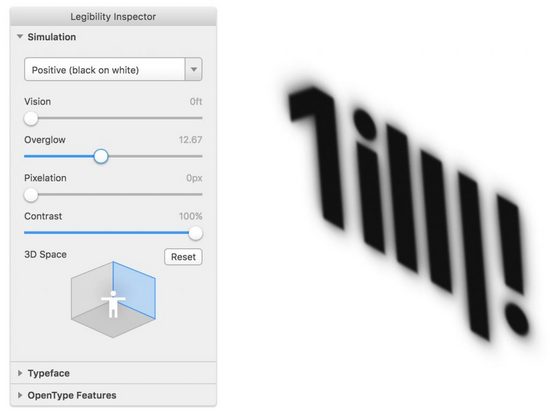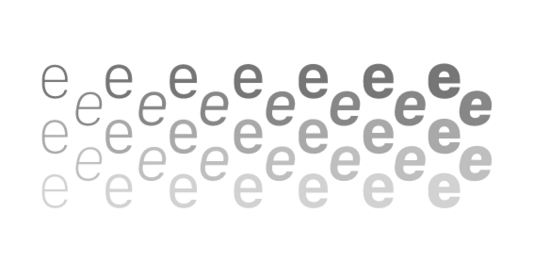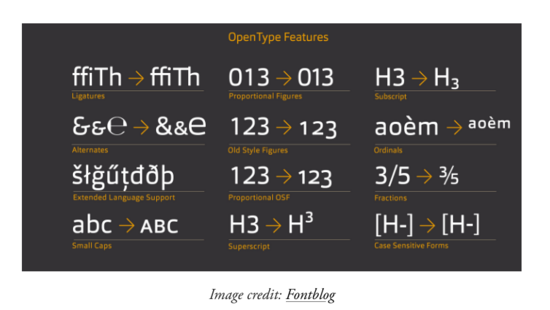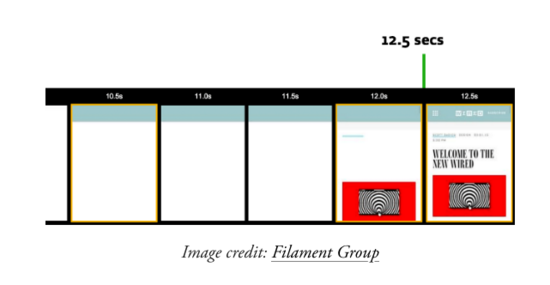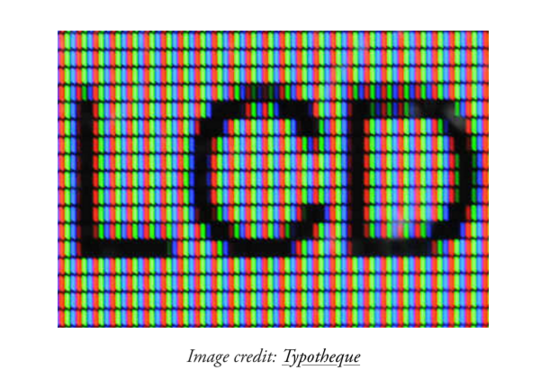
界面设计中,关于字体设计的10 个锦囊
字体作为界面设计的一个元素,对用户的阅读体验起着至关重要的作用。本文是 UI 设计师 Viljami Salminen 分享的用户界面字体设计的基本规则和技巧。
早在 2004 年,我才刚开始工作的时候,sIFR 非常火。sIFR 是由 Shaun Inman 开发、可以电影短片中嵌入定制字体的一种技术,它能被 JavaScript 和 CSS 调用。当时,sIFR 基本上是唯一一种能在 Firefox 或 Safari 浏览器中使用定制字体的技术。随着 2007 年 iPhone(不需要 flash)的推出,基于 Flash 格式的这种技术很快就过时了。
2008 年,浏览器终于开始支持新的 CSS3 字体设计规则了。早在 1998 年,这种字体设计规则就被写入 CSS 标准中了,但后来被移除了。我还记得,当我说服我的一个客户使用这种新的字型规则时候的兴奋心情,当时,浏览器已经开始支持能够提升用户体验的「渐进增强(Progressive Enhancement)」技术了。
自从涉足这个行业,我开始越来越喜欢研究字体,以及与字体设置中相关的微小细节。在这篇文章中,我打算分享一些我了解到的基础知识,希望能为用户界面的字体设置提供帮助。
第一代GUI
虽然字体的历史可以追溯到大约 5000 年前,但是图形用户界面的出现还不到 40 年。一个重要转折点发生在 1973 年,Xerox 推出了计算机 Alto,大体上奠定了今天图形用户界面的雏形。当时 Alto 被视作是计算机的未来,在 10 年之后,同类 GUI 产品才进入大众市场。
80 年代,Xerox 推出了以 Alto 为基础的升级版  Xerox Star ,是世界上第一个商用的 GUI 操作系统。
无论是 Alto 还是  Xerox Star 最终都没有大肆流行,不过,二者对苹果和微软在鼠标驱动 GUI 的革命性创新产生了极大地影响。几十年之后,也就是 1984 年,乔布斯推出了第一代 Mac OS。
Macintosh 的推出意味着,大众第一次可以使用定制字体了。第一代 Mac 预装了多款经典字体,在接下来的几年中,越来越多的字体厂商除了发布传统字体之外,还会推出相应的数字版本。
当我们检视这些早期的图像用户界面的时候,我们发现,其中大部分元素都是用手写的。这些 GUI 都是纯文本,即一个个字母的纯文本集合体。
我们再以同样的方式观测现代的用户界面。在现代的交互界面中,文本即界面,字体设计则成为主要的设计规范。
字体即界面设计的基石
在用户界面中,每一个单词和字母都至关重要。好的字体等于好的设计。字体成了界面设计的基石,而我们设计师,则是这些这类「信息基石」的修造者。
观察下面这个例子,想象一下,把以下图片中的元素拆解开来,看看会是什么样子——一个个单词、两张图片、几个图标。
作为设计师,我们的工作并不是在屏幕上随机摆弄几个元素,让他们看起来美观漂亮就行了,而应从最重要的部分着手,即字体和内容,以及由此产生的相关细节。这才是我们作为设计师的核心技艺。
字体的可辨识性也十分重要。关于这一点,一开始看起来似乎不重要,特别当辨认单词是如此容易的时候——人类大脑辨识出某一个单词所需的时间还不到一秒钟。但是,当需要辨认的单词和字母组合变多,字体的重要性就显而易见了。
虽然在界面设计上,有很有多微小的细节需要考虑:比如平衡、定位、层级和结构,但是有了好的文案和字体,就成功了 95% 。
一个优秀的设计师懂得:网页上的文字不仅仅作为内容而存在,它还是用来交互的界面。
– Oliver Reichenstein
我们人类是如何阅读的?
既然字体设计如此重要,那么我们就应该花点时间学习「我们人类是如何阅读的」,以及「字体设计是如何影响设计策略的」。
在阅读 Billy Whited 的文章「Setting Type for User Interfaces」时, 我有一个重要发现,即阅读效率和文本的数量有很大关系。这意味着,在阅读少于 20 个字母的单词时,单独提出来阅读相比于放在长句中阅读速度会更慢。这是因为,当我们阅读长句时,眼睛并不是顺着句子中单词一个一个看的,而是有选择性跳读的,这个动作被称作「扫视」。
跳读提升了阅读效率,使阅读时可以忽略掉一些功能性单词成为可能。这点要深记于心,因为用户界面上大都是一个个独立的单词,也就意味着「扫视」在 UI 设计中不起作用了。
因此,当我们明白细微到每一个字母都会对阅读体验产生重要影响时,我们也就明白为什么字体的选择那么重要了。
过去,我们认为我们是以单词的外形轮廓来辨识单词的,这个理论被称为「Bouma shape 伯马形」,后来研究发现,这个观点并非完全正确,字体的可读性和辨识度并不单单由字体的整体轮廓决定。我们更应该重视字形本身。
决定字母可读性的因素是什么?
首先,回答这个问题似乎有点难。阅读是一种习惯,有良好阅读习惯的人肯定读得越顺畅。我们怎么可能知道影响字母可读性的因素是什么?为了便于理解,我们需要首先把句子分解成单词,单词分解成字母,字母分解成更小的元素,然后解剖出更多细微层面的细节。
2008 年, 维多利亚大学心理学院进行了一次实证研究,显示了大小写拉丁字母适合阅读的最佳范围。
从这个研究中,得出了一些有趣的结论。首先,线条终止的方式对于字母辨识起着至关重要的作用。
上图显示了辨识单词时最受人眼关注的区域范围。在设计字体的这个区域时,不仅应该考虑阅读的一般性和习惯性,而且需要把每个字母的差异性也考虑进来。
2010 年, Sofie Beier 和 Kevin Larson 发起了另一个研究:对一些容易被误读的单词变体进行了测试。
这个研究发现,虽然有些字母在尺寸、字重和特性上相同,但是他们在辨识度上却各不相同。结果显示,细长的字母拉宽一些,就会变得更具辨识度,而 X 字高的字符,如果增加升部和降部的长度则更具辨识度。
我为最近一个项目开发了一款名叫 Legibility 的 App ,这款工具可以对字体设计进行辨识度的模拟测试。通过对文字加上不同的滤镜效果(比如模糊、微亮和像素化效果),模拟出不同的阅读环境。目前还是 beta 版,支持Chrome, Opera 和 Safari。
UI字体设计应该注意哪些方面?
在了解人类阅读原理和字母可辨识度的概念之后,对于 UI 设计我们有了一个更好的全局观。以下是我总结的几点:
1. 辨识度
辨识度是需要考虑的首要因素。字母的格式要清晰、可辨认。在 UI 设计中,清晰可见的字母更具辨识度。很多无衬线字体(San Serif),包括 Helvetica ,大写的字母 I 和小写的 l 字母难以区分,对于 UI 设计来说是非常不好的体验。
比较左边的 Source Sans Pro 字体和右边的 Helvetica 字体。右边的 Helvetica 字体中,前三个字母几乎是一模一样。而左边的 Source Sans Pro 字体表现更佳。甚至有人认为,Helvetica 不适用于任何 UI 设计,不过它本来就不是为屏幕显示而生的。
Helvetica 真的弱爆了。它不是为小屏显示而设计的。像「milliliter」这样的单词显示效果就很差。
– Erik Spiekermann
当年苹果曾经暂时使用过  Helvetica 作为其主要的 UI 设计字体,不过这一举动曾给一些用户带来了阅读上的问题。不过,正是因为这次事件才导致了苹果后来设计了 San Francisco 字体。 San Francisco 字体是为屏幕而生, [2] x-height 比 Helvetica 字体更高,有着更宽的字距,单个字母更容易辨认。
2. 低调
一个完美的 UI 字体让人意识不到它的存在,绝不会喧宾夺主。字体应该是方便用户完成任务的,而不应为用户添加认知上的负担。
3. 灵活度
UI 字体应该具有一定的灵活度。记住,我们是在为各种不同的媒介设计用户体验,我们无法掌握的是——用户的能力、应用场景、所用的浏览器、屏幕大小、连接速度,甚至使用的输入方式。
我们选择使用的设计字体应该支持尽可能多的使用场景,能在不同大小、各种不同的设备、以及特定的小屏设备上运行良好。比如 Sans serifs 字体能在低分辨率的小屏上运行良好。
4. 高的x-height
X 字高是指小写字母「x」的高度。x-height 越高,小屏阅读体验就越好。但字高也不能过大,要不然 n 和 h 难以区分。
5. 宽比例
比例是指一个字符的高和宽的比值。宽度的比值越大,字体辨识度越好,小屏阅读体验也越好。
6. 宽松的字母间距
一个重要的原则是,字母之间的间距要比 [3]「字柜」(counter)要小。
字母周围的空间和字母的内部空间同样重要。字母如果相距太近读起来很费劲。一个好的 UI 字体应该要给字母之间留有充分的呼吸空间,留有一些空间,建立起稳定的节奏。
另一方面,如果间距太大,则会打破单词的整体性。一个重要的原则是,字母之间的间距要比「字柜」(counter)小。
7. 平顺的笔画
好的 UI 字体应该是笔画平顺。不够平顺的字体在大屏上看起来可能还好,一旦在小屏上显示,细长的笔画就难以辨认。另一方面,像 Arial 和 Helvetica 这样的字体,由于字母笔画粗细几乎一样,因此让阅读变得尤其困难。
所以,需要在这两者之间达到平衡。下面两个案例,你觉得哪个更好?
8. 支持OpenType功能
确保你选择的字体支持 OpenType 功能这一点很重要,因为它能为我们提供更多的自由度。支持 OpenType 功能也表明可以很好地支持不同的语言和特殊字符。
对于我来说, OpenType 功能最有用的一点是「表格数据」,它是指相同宽度的一连串数字。计时器、计算器或者 IP 数字的设计中,可以用到这个功能。
9. 字体回退机制(Fallback)
下面这个案例你可能非常熟悉。在加载未完成时,网页字体不能完全显示出来。
要解决这个问题,只需要以非阻碍的方式来加载字体,这样可以大大减少内容加载的时间。这样做的缺点是,需要在默认系统字体中设置回退字体,默认系统字体是在页面加载时屏幕显示的字体。
整体来说,我认为,UI 字体的未来将与传感器有关,以及字体将能根据传感器搜集到的数据进行格式的调整。未来,新的字体设计工具会在工作流中整合智能算法,能对不同场景进行自动识别。
开放设备实验室 (Open Device Lab),旨在帮助网页设计师在各种不同的移动设备上测试作品的效能和表现。
x-height: 小写字母的高度(尤其是小写x),不包括升部和降部。
「字柜」是指字符中的负空间。